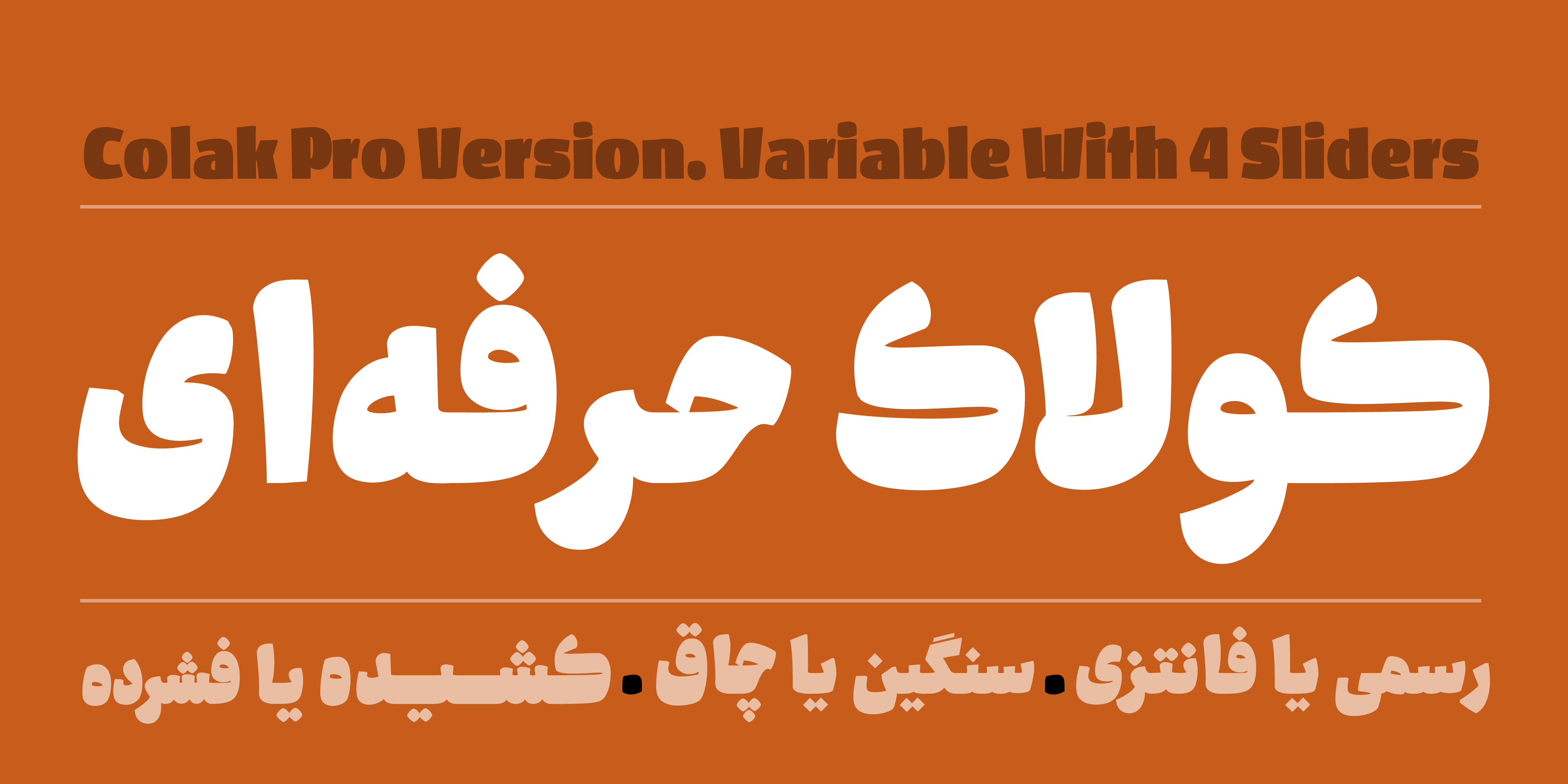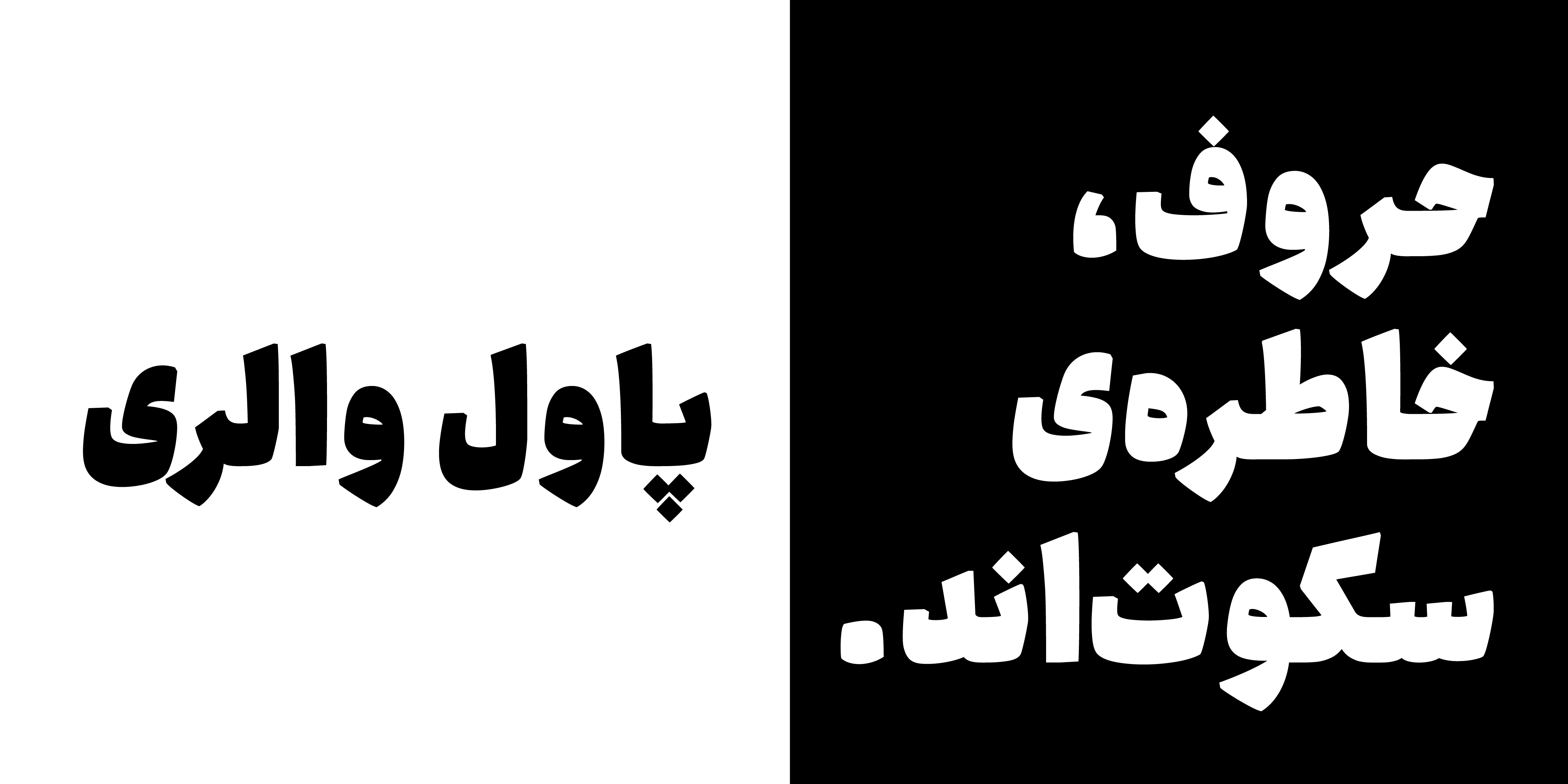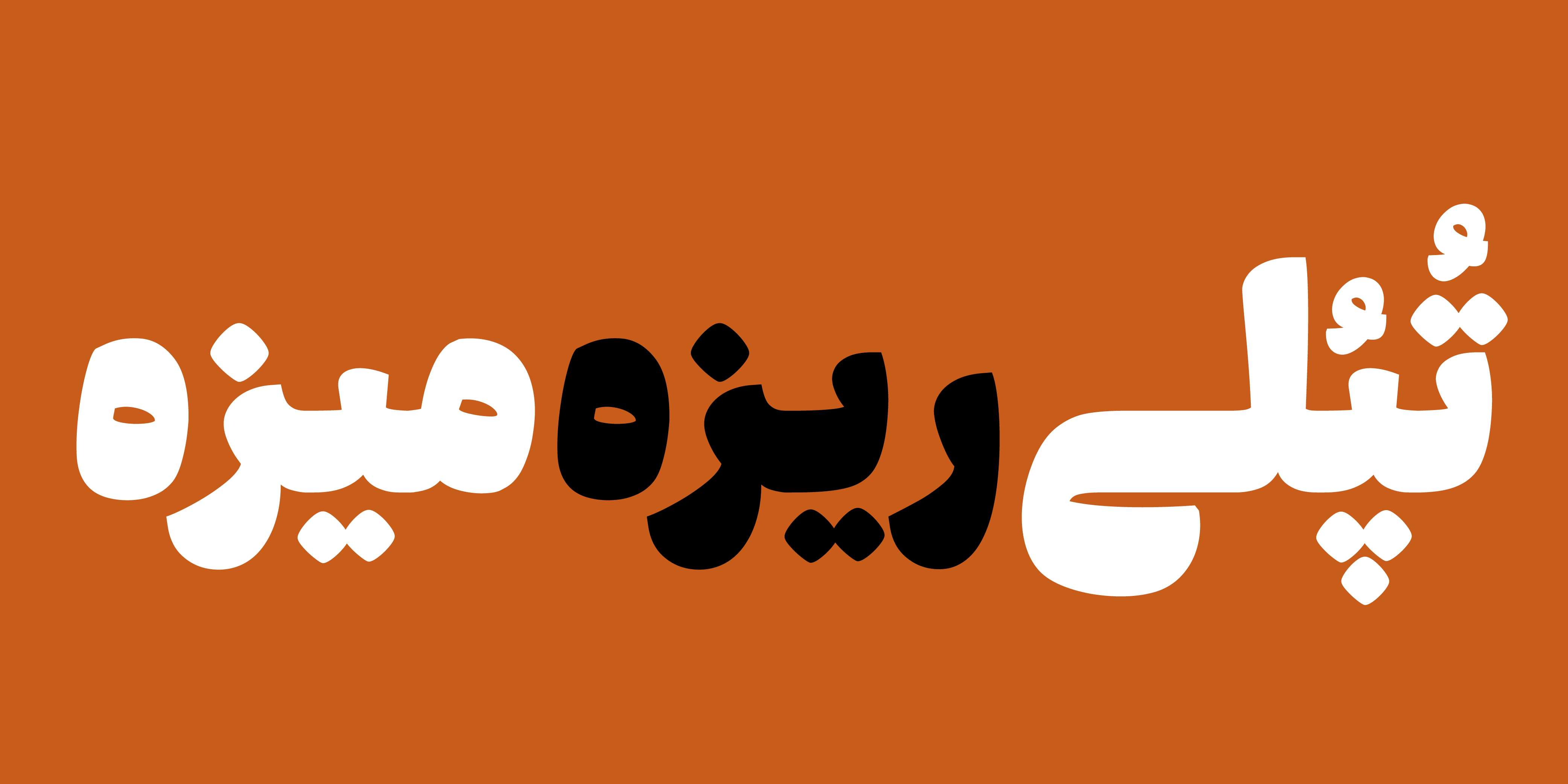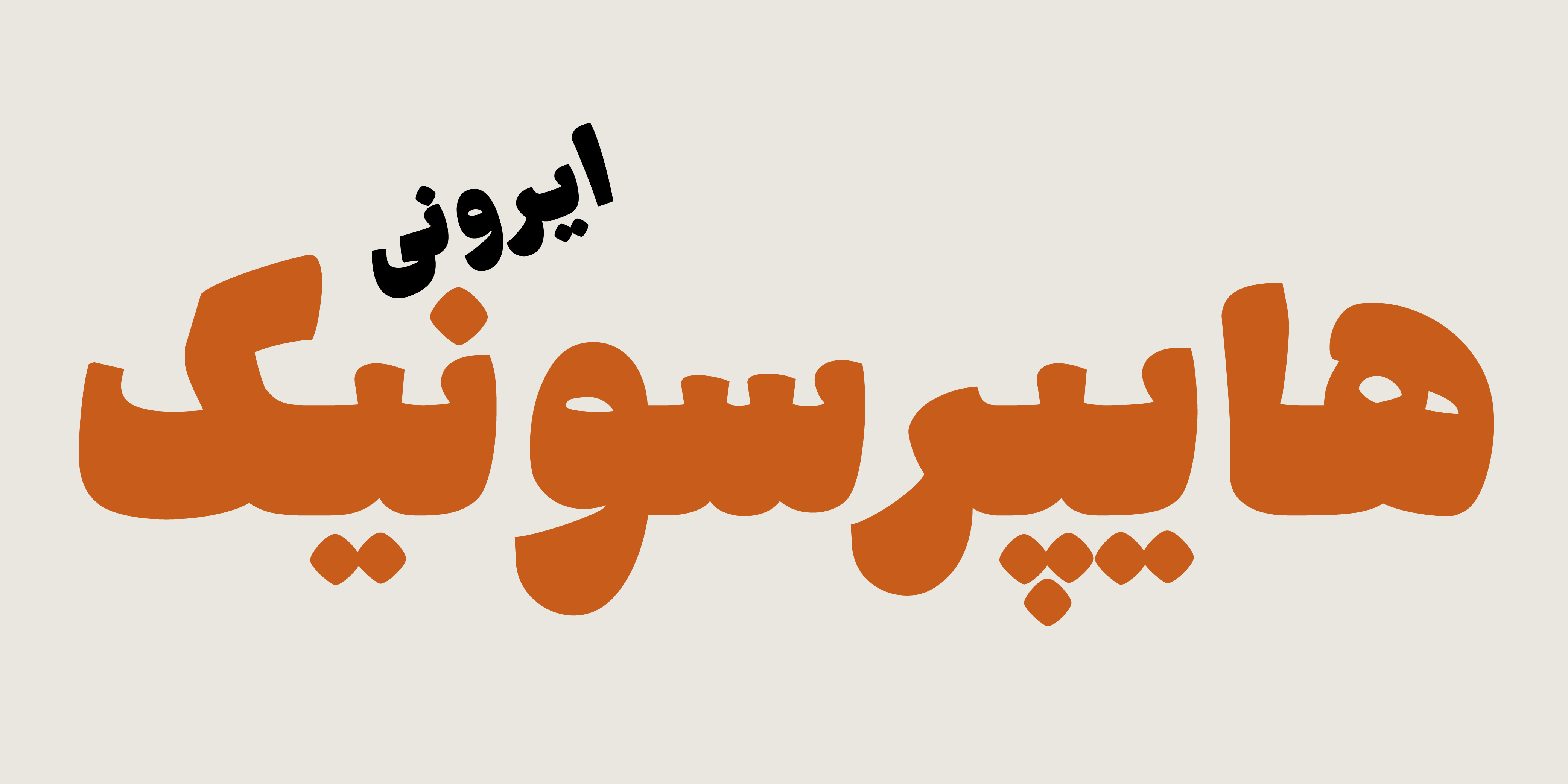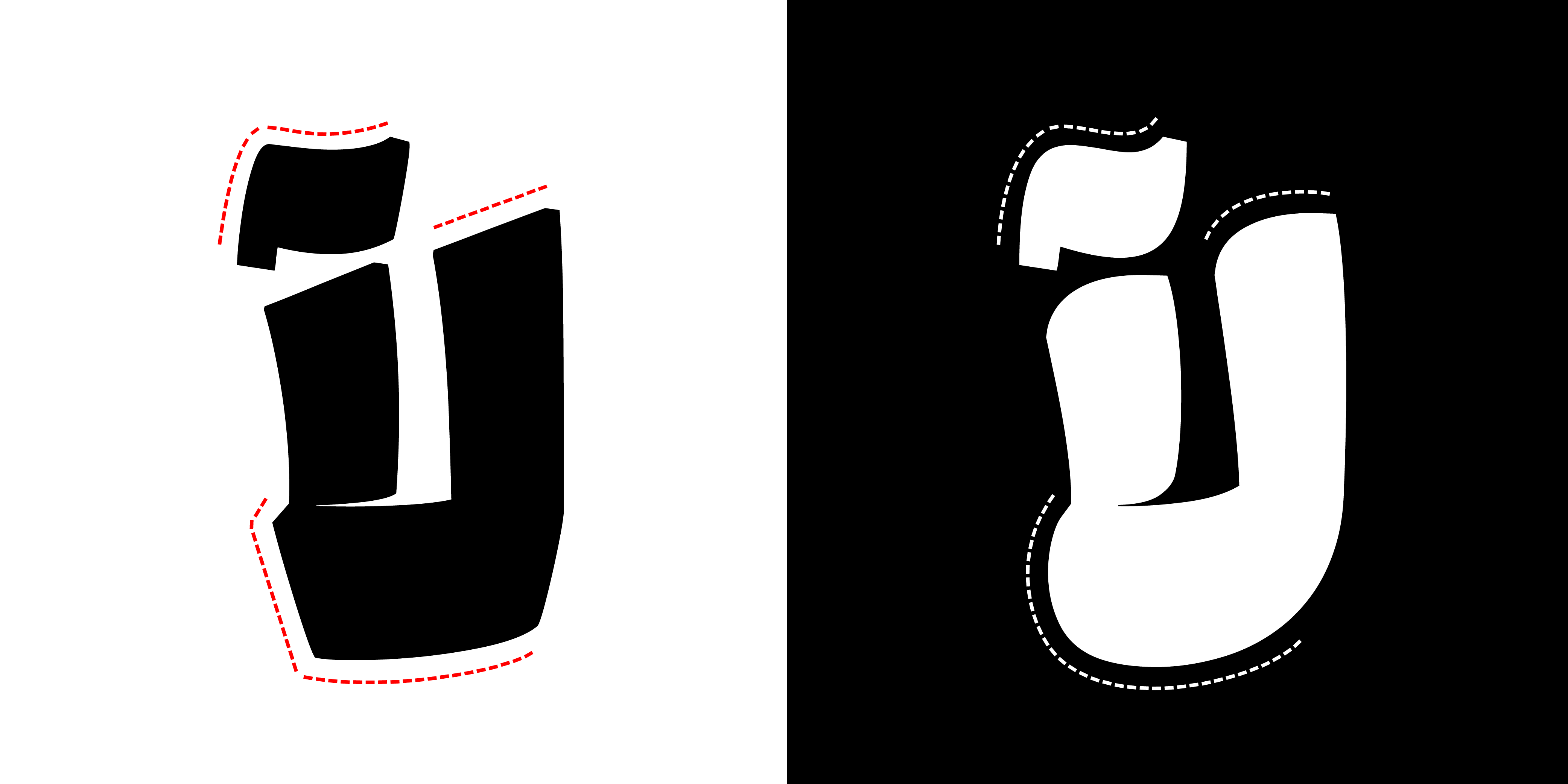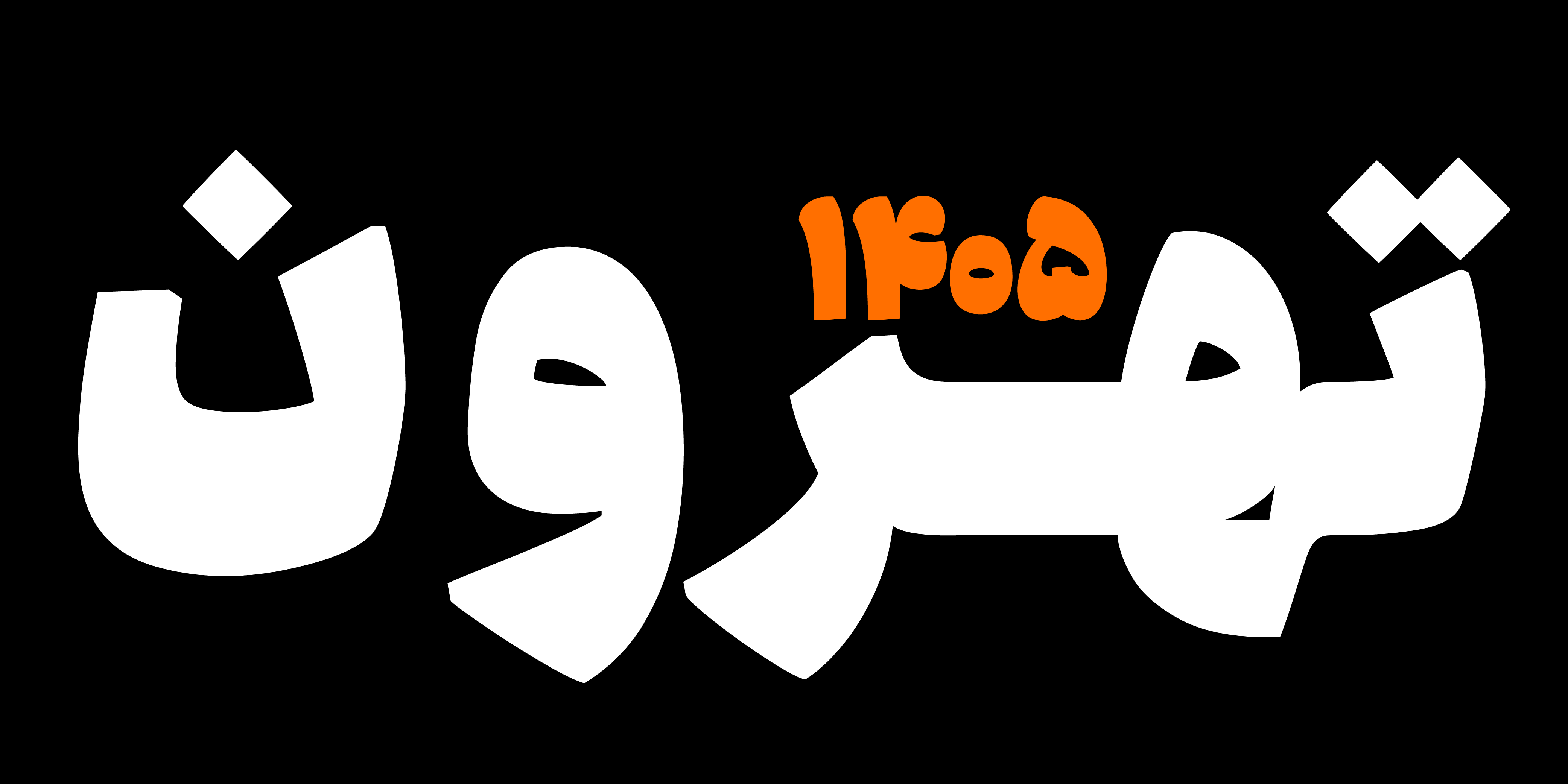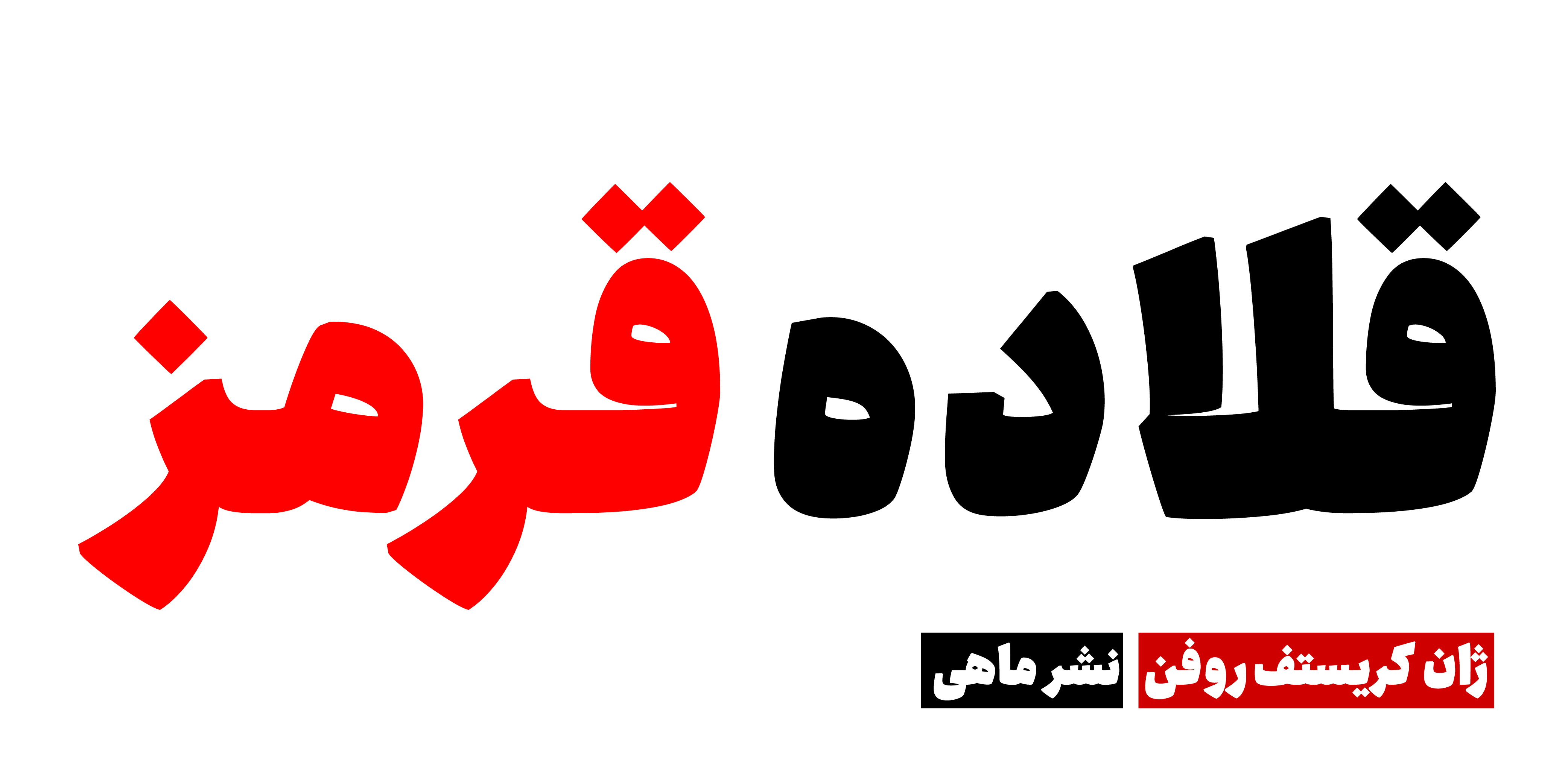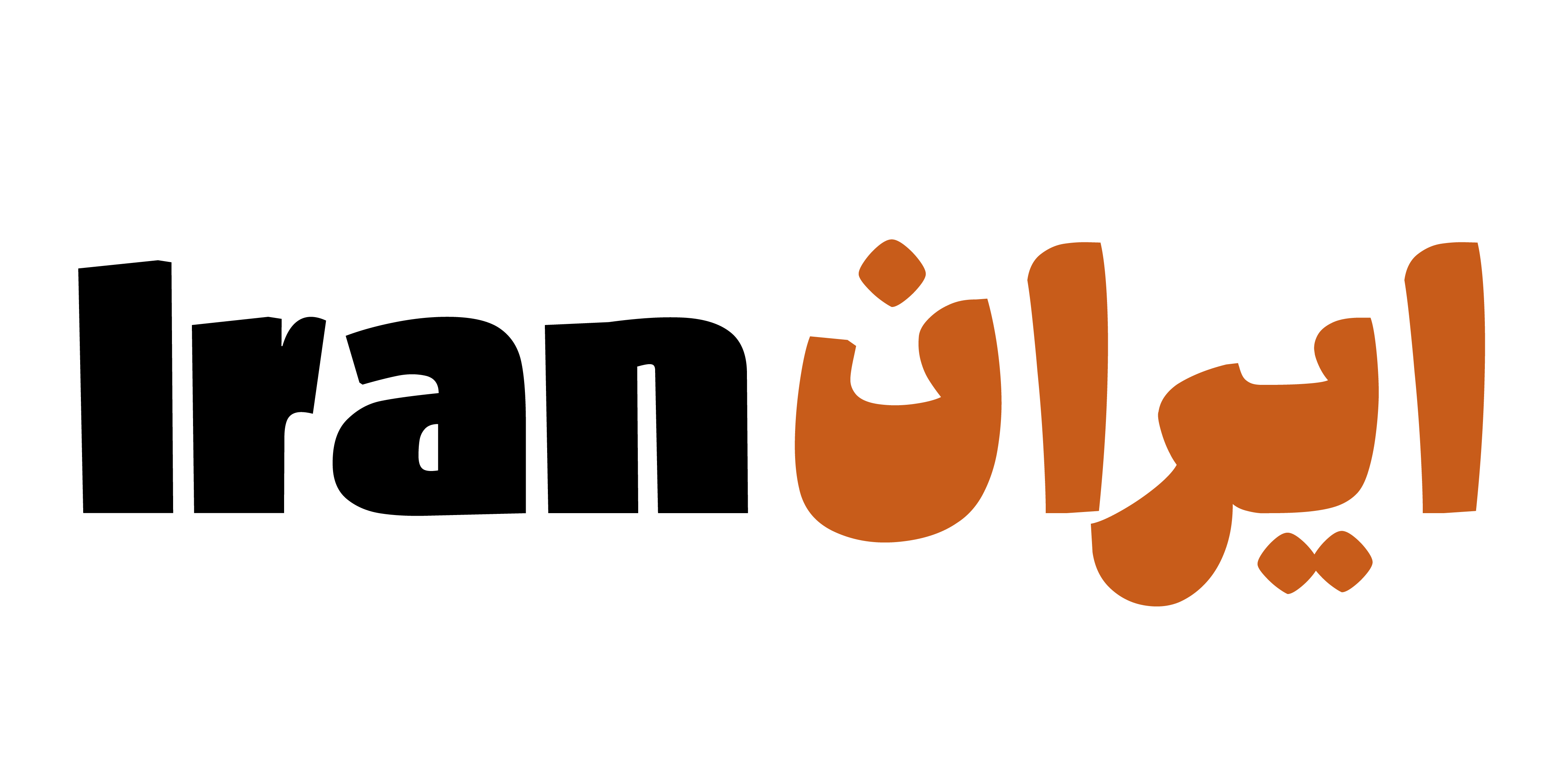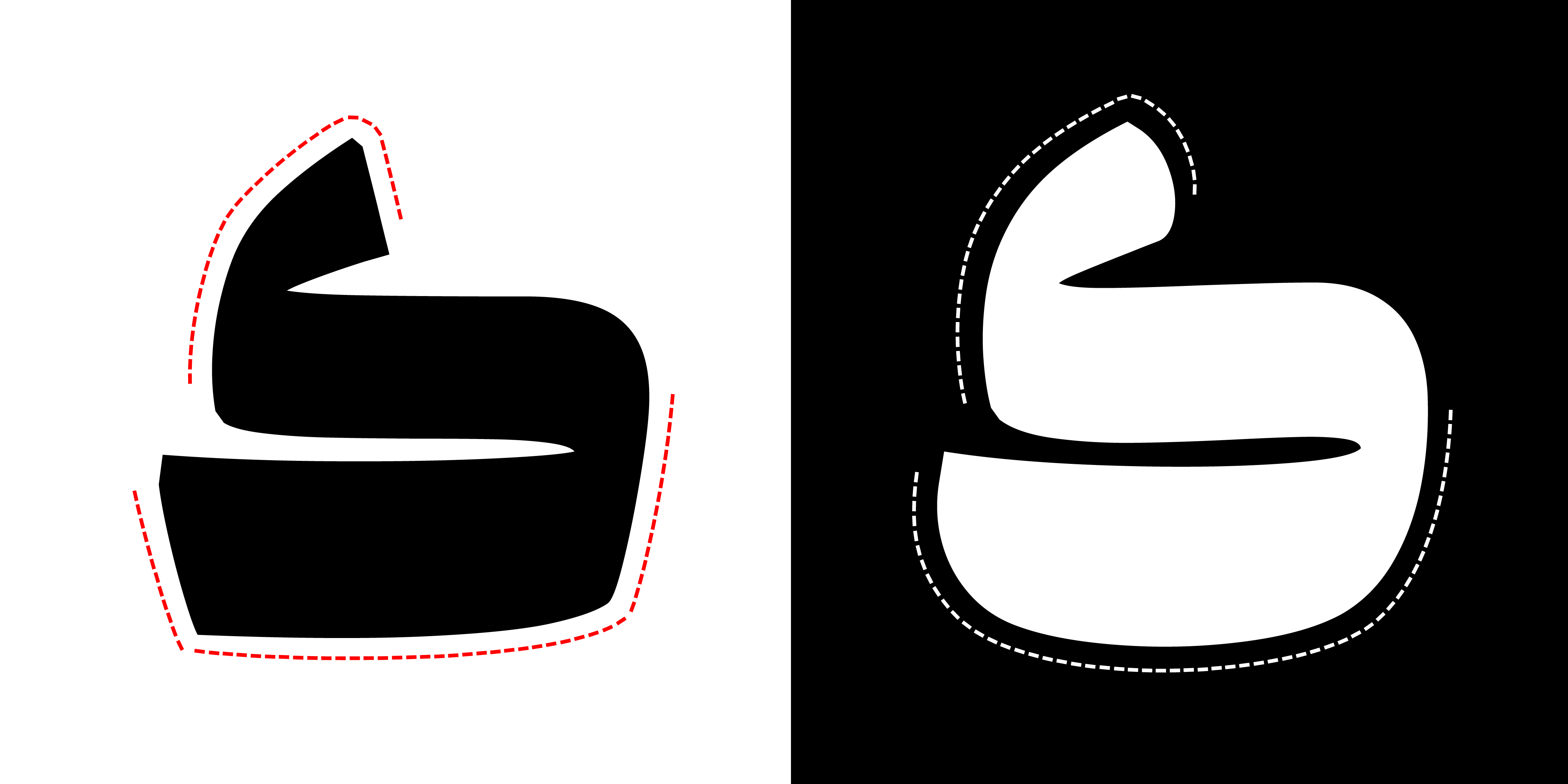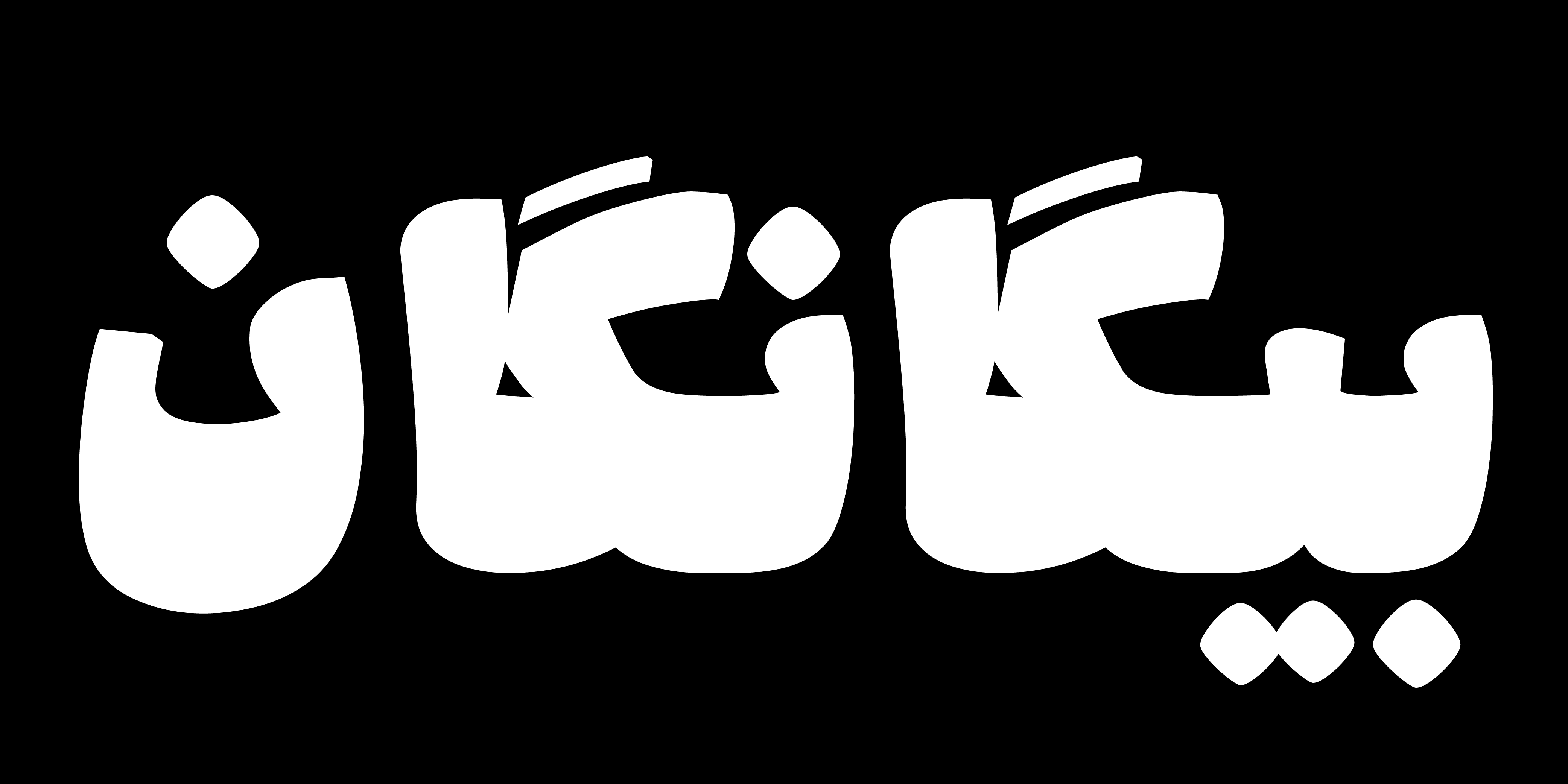
ویژگی وریبل فونت|متغییر Style (سبک)
- Style(سبک): به شما امکان میدهد مجموعه از حالتی سخت و تیز به فرمی سیال و دوستانه بین دو سبک مختلف از یک فونت را داشته باشید. این ویژگی برای طراحیهایی با روحیه صمیمی و انسانی، ایدهآل است.
ویژگی وریبل فونت| متغییر Weight(وزن)
- Weight(وزن): قابلیت تنظیم وزن فونت از حالت سنگین تا بسیار سنگین(چاق) را تغییر میدهد و قدرت بصری بیشتری به حروف میبخشد.
ویژگی وریبل فونت|متغییر Compact (فشردهسازی)
- Compact(فشردهسازی): این متغییر به شما اجازه میدهد فاصله بین حروف را کاهش دهید و متن بیشتری را در فضای کمتر جای دهید، بدون اینکه خوانایی فدا شود. این ویژگی به معنای حالت Condensed نیست. بلکه فضای منفی بین فرم هر کارکتر و فواصل بین آنها را کاهش میدهد و در برخی از کاراکترها عرض حروف نیز کمی کمتر شده است.
ویژگی وریبل فونت| متغییر Keshida (کشیدگی)
- Keshida(کشیدگی): امکان تنظیم طول حروف را برای تاکید بصری و ایجاد زیباییشناسی خاص در عناوین فراهم میکند. این ویژگی برای کاراکترهایی که در حالت وسط فرم، اتصال دوطرفه دارند، از سمت چپ قابلیت اعمال دارد.
«کولاک پرو» در مقایسه با «کولاک» همچون یک جعبهابزار جامع و قدرتمند برای طراحی عنوانها و تیترها عمل میکند. ویژگیهای برجسته آن عبارتاند از:
- ارائه دو سبک رسمی و فانتزی برای ایجاد تنوع در فرم حروف و کاربری در فضاهای مختلف
- برخورداری از چهار متغیر وریبل که با استفاده مستقل یا ترکیبی از آنها، فرمهای متفاوتی از حروف قابل تولید است
- دارای وزن فوقسنگین (Fat) که با کمک متغیرهای وریبل قابل استفاده و تنظیم است
- پشتیبانی از حروف جایگزین و امکانات اُپنتایپ (Ligatures)
ترکیب این قابلیتها و پارامترهای متغیر، انعطافپذیری طراحی را بهطور چشمگیری افزایش میدهد و به طراحان، تایپوگرافرها و کاربران امکان میدهد علاوه بر دسترسی به چندین حالت نوشتاری، خروجی دقیقتر و متناسبتری با نیاز پروژه خود ایجاد کنند.